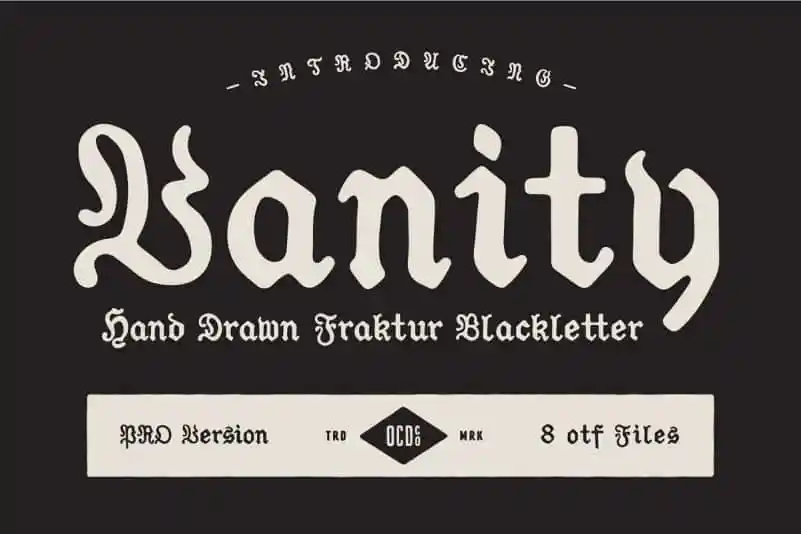
Vanity Display Font é uma elegante escolha para qualquer designer que busca dar ao seu trabalho aquela sensação única de mão feita, mas com um toque moderno e sofisticado. Com seu excepcional design blackletter, este tipo digital transmite uma paixão genuína pela tipografia vintage, misturando elementos romanos e serifos para criar texturas reais que remetem à era da manufatura artesanal. Esta fonte conta com oito estilos cuidadosamente criados, cada um oferecendo uma experiência visual única. O uso de ligaduras adiciona ainda mais profundidade aos caracteres, tornando a Vanity Display Font perfeita para trabalhos que precisam se destacar e transmitir uma mensagem poderosa ou emotiva. Com sua rica história na tipografia manufaturada e seu moderno design blackletter, este tipo é ideal para criações de marca, artigos de arquitetura ou qualquer trabalho em que você deseja dar aquele toque único e autêntico à sua composição visual.